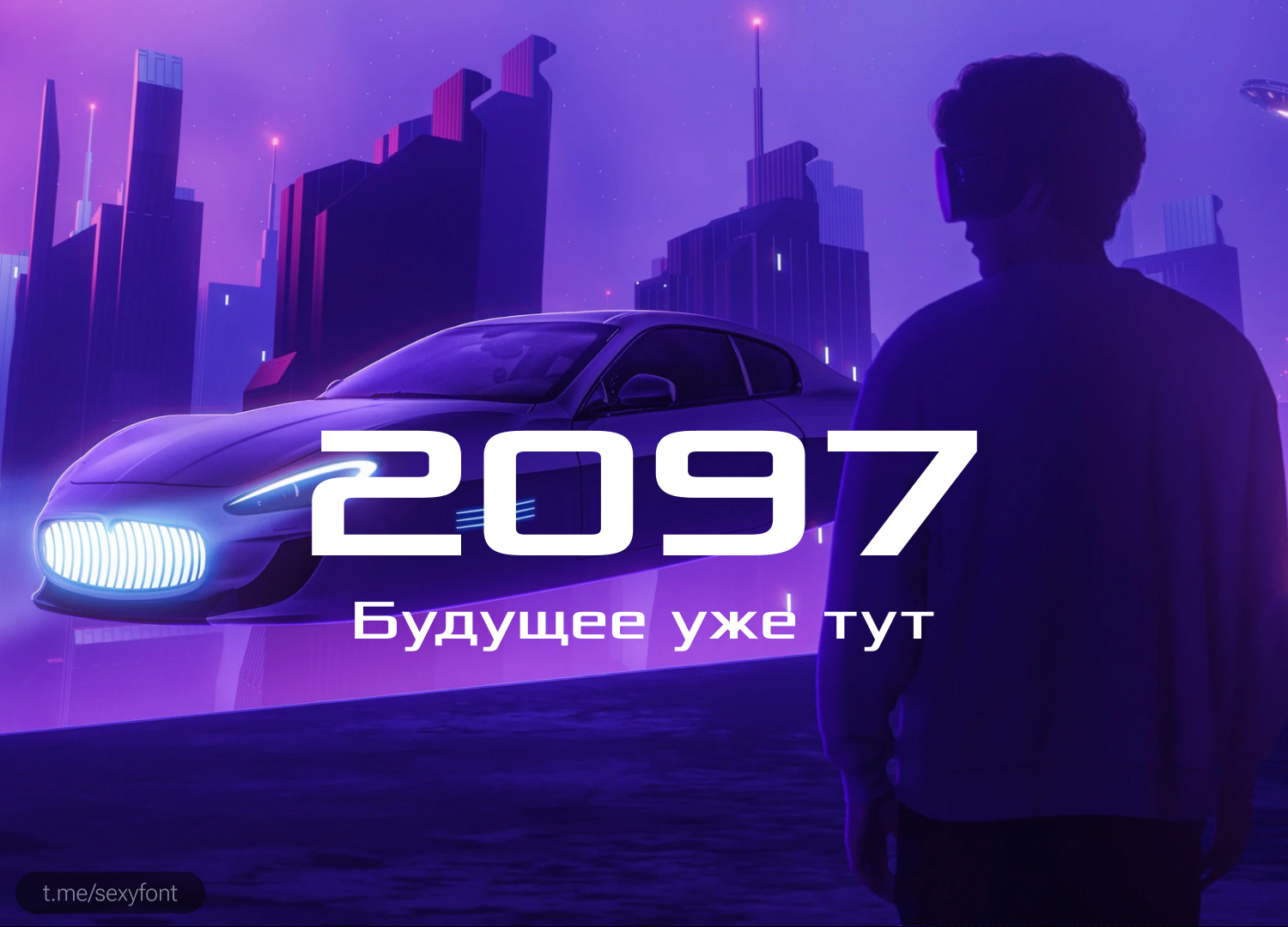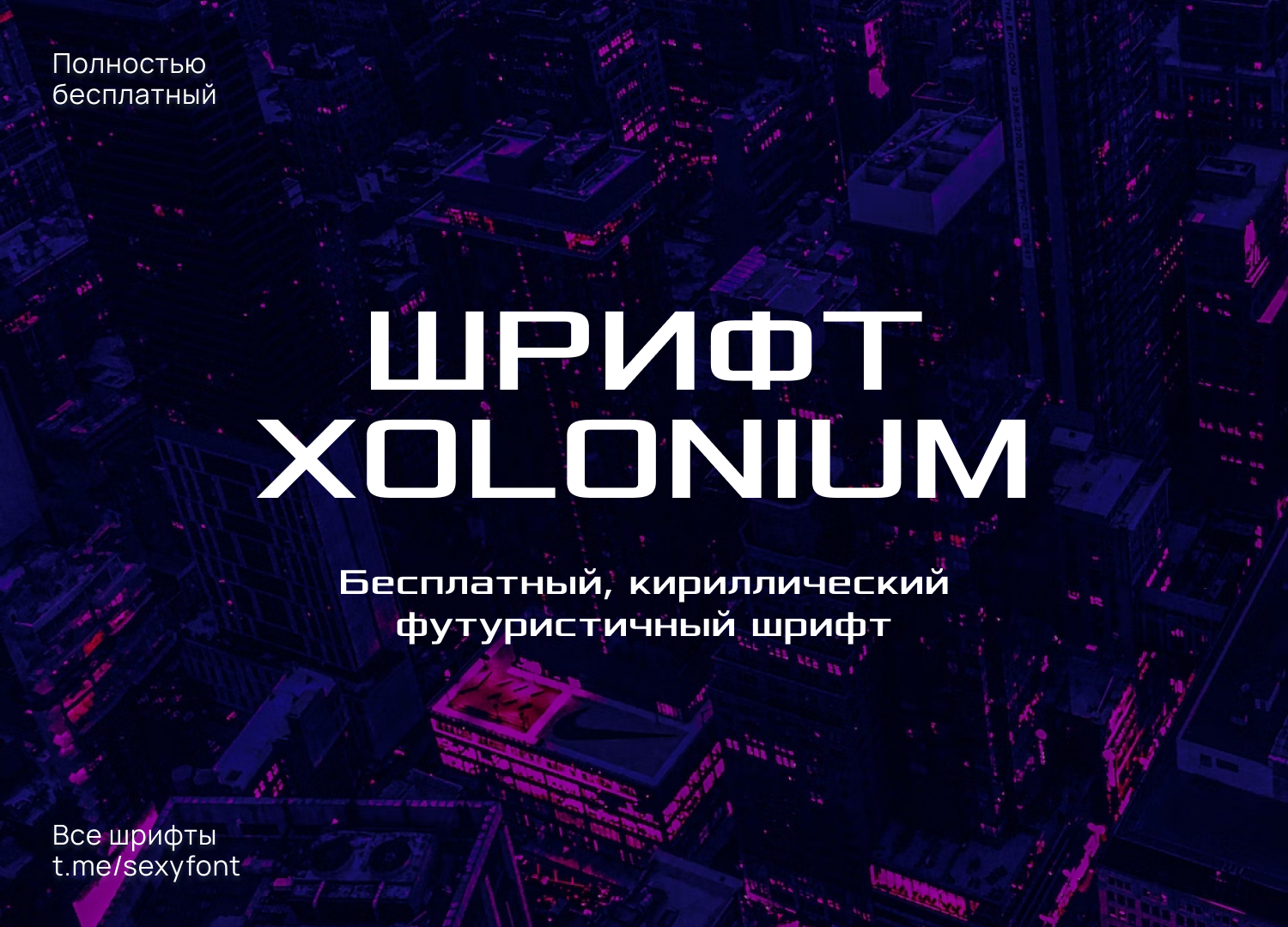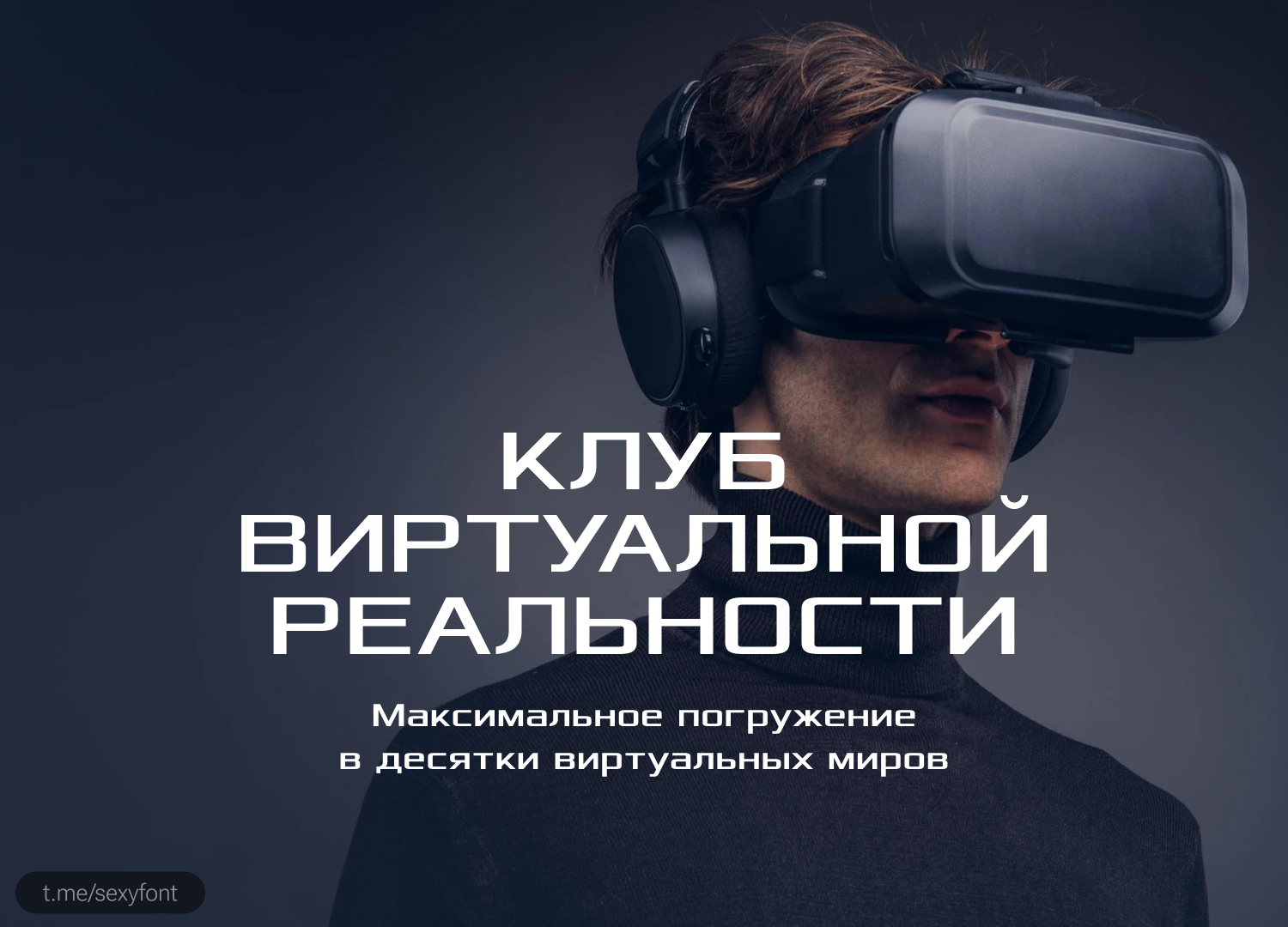
Шрифт Xolonium
Футуристичный шрифт Xolonium. Главное, что он хорошо читается, как в крупных заголовках, так и в обычных абзацах. Бесплатный для личного и коммерческого использования. Автор: Severin Meyer